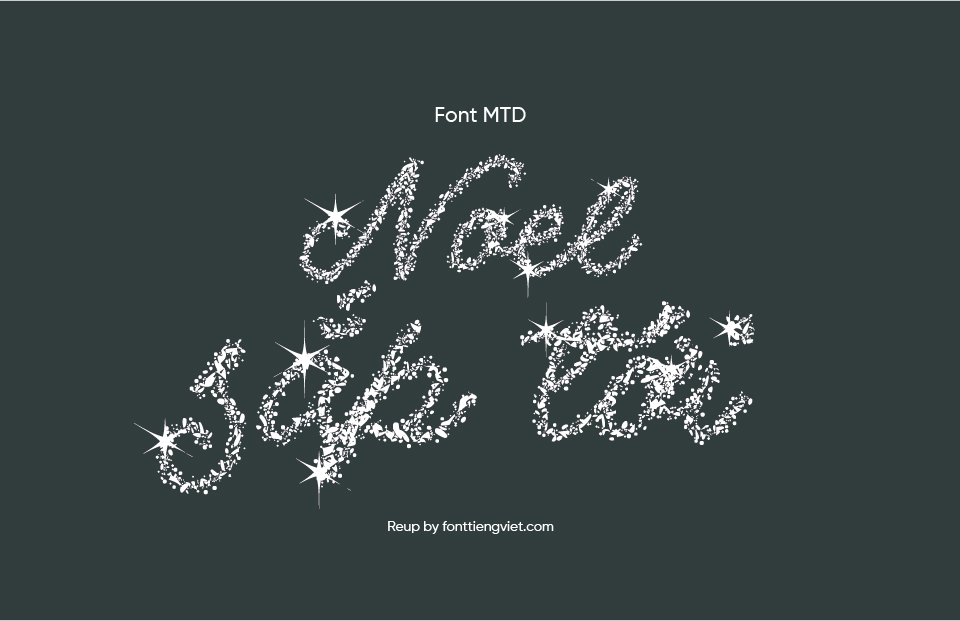
Font Việt hóa MTD Christmas Miracle – Giáng sinh
Font Việt hóa MTD Christmas Miracle – Giáng sinh lung linh sắc màu lễ hội
Sức hút của bộ Font Việt hóa MTD Christmas Miracle – Giáng sinh
Mùa lễ hội cuối năm luôn là thời điểm tuyệt vời để các nhà sáng tạo làm mới hình ảnh thiết kế của mình. Với sự ra đời của Font Việt hóa MTD Christmas Miracle – Giáng sinh, bạn sẽ sở hữu một công cụ đắc lực để thổi hồn vào các tấm thiệp mừng, biểu ngữ hay các bài thuyết trình học đường. Đây là bộ Font Miễn Phí chất lượng cao, mang đậm phong cách cổ điển xen lẫn hiện đại, giúp thông điệp của bạn trở nên ấm áp và gần gũi hơn bao giờ hết.
Đặc điểm nổi bật của phông chữ
Bộ phông chữ này gây ấn tượng mạnh nhờ những đường nét uốn lượn mềm mại, mô phỏng lại nét bút lông nghệ thuật. MTD Christmas Miracle đã được tinh chỉnh kỹ lưỡng về dấu tiếng Việt, đảm bảo không xảy ra lỗi hiển thị khi soạn thảo nội dung dài. Sự kết hợp giữa các nét thanh nét đậm tạo nên sự uyển chuyển, rất phù hợp cho các chủ đề trang trí liên quan đến tuyết rơi, cây thông và những điều kỳ diệu của đêm Noel.
Ứng dụng Font Việt hóa MTD Christmas Miracle – Giáng sinh trong giáo dục
Đối với học sinh và giáo viên, việc sử dụng font chữ phù hợp giúp bài giảng trở nên sinh động. Bạn có thể dùng phông chữ này để làm tiêu đề cho báo tường, trang trí lớp học hoặc tạo ra các phần quà tinh thần cho học trò. Sự rõ ràng và đẹp mắt của nó giúp người xem dễ dàng tiếp nhận thông điệp yêu thương trong dịp cuối năm.
Kết luận về bộ phông chữ lễ hội